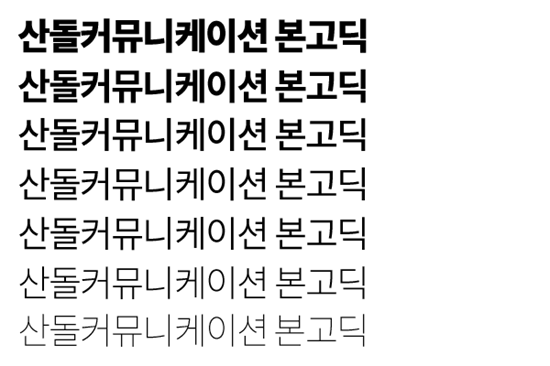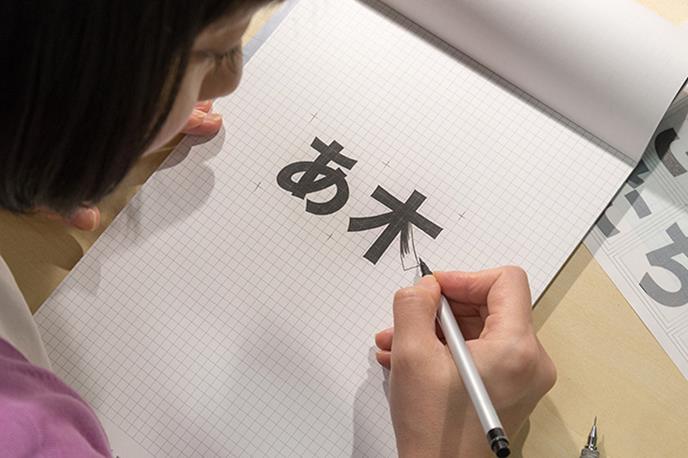
산돌+Adobe+Google, 글로벌 오픈소스 서체 ‘본고딕’ 출시
산돌커뮤니케이션(이하 산돌)이 Adobe, Google과 함께 한중일 오픈 소스 서체인 ‘본고딕(Source Han Sans)’을 7월 16일 출시했다. 성공적인 한중일 통합서체 개발을 위한 본고딕 프로젝트는 산돌커뮤니케이션이 한글 제작에 참여하였으며 일본의 이와타, 중국의 창저우 시노타입 등 총 5개 기업의 공동작업 형태로 진행됐다.
Adobe-Google-산돌, 공동 프로젝트로 뭉치다
사회 환원의 비전을 가진 Adobe는 ‘누구나 사용 가능한 오픈 소스 서체 개발’에 지속적 관심을 가지고 있었고 Google 역시 같은 뜻으로 본고딕 프로젝트에 함께했다. 전세계 모든 정보를 체계화해 언제 어디서 누구든 용이하게 정보에 접근하게 하는 것이 Google의 목표이기 때문이다.
성공적인 한중일 통합서체 개발을 위한 본고딕 프로젝트는 산돌커뮤니케이션이 한글 제작에 참여하였으며 일본의 이와타, 중국의 창저우 시노타입 등 총 5개 기업의 공동작업 형태로 진행됐다. 개별 서체의 퀄리티는 물론 서로 다른 언어의 서체가 한데 어우러졌을 때의 조화까지 고려해야 하는 만큼, 서체 개발업계에서도 매우 드문 기획이었으며 그만큼 많은 이들의 이목을 집중시켰다.
본고딕은 어떤 서체인가?
▲ 다양한 언어로 쓰인 본고딕 (이미지 출처 – Typekit Blog)
▲ 위쪽부터 Heavy, Bold, Medium, Regular, Normal, Light, ExtraLight
본고딕은 한국어, 일본어, 중국어 번체, 중국어 간체, 라틴어, 그리스어, 키릴 자모가 모두 포함된 글로벌 오픈 소스 서체다. 언어 당 65,535개의 글립(Glyph, 글자 하나의 모양에 대한 기본 단위)이 포함되고 모든 언어를 합쳐 총 50만개 글립에 이르니, 지금까지 제작된 서체 중 최대 규모라 할 수 있다. 더불어 모든 언어의 서체가 각각 ExtraLight, Light, Normal, Regular, Medium, Bold, Heavy의 7가지 굵기를 가지고 있어 더욱 폭넓게 사용할 수 있다.
▲ 본고딕 서체 디자인 작업을 하고 있는 료코 니시즈카의 모습 (이미지 출처 – Typekit Blog)
기능 및 디자인 측면에서 본고딕을 키워드로 표현하자면 바로 ‘가독성’과 ‘우아함’. 간소화된 자획과 일관된 두께로 태블릿 PC나 모바일 등 작은 화면과 장문의 텍스트에서 가독성을 살린다. 그에 더해 간소화된 형태에도 불구하고 전통 고딕 서체 본연의 우아함을 잃지 않았다는 평가도 얻고 있다. 또한 아시아권을 아우르는 한중일 통합 서체답게 지역에 따른 한자 글꼴 차이를 완벽하게 지원하며, 서로 다른 언어의 서체를 사용해도 조화를 잃지 않으니 글로벌 컨텐츠를 제작해야 하는 디자이너들을 만족시킬 수 있을 것으로 예상된다.
Adobe-Google-산돌, 본고딕에 관한 말말말
본고딕의 저작권을 소유한 Adobe는 검증된 서체 디자인 경험을 바탕으로 자동화 등 전문 기술을 제공했다. Adobe 서체 개발 수석 켄 룬드 박사는 “본고딕이라는 오픈 소스를 통해 콘텐츠 제작자가 원활하게 작업하고, 동아시아 사용자에 수준 높은 서비스를 제공할 수 있을 것”이라고 말했다. 이로써 본고딕은 Adobe 창립 25주년을 맞이해 101번째 Adobe 오리지널 서체가 되었다.
Google은 적극적 의견, 리소스, 전문 기술, 자금까지 본고딕 제작 프로젝트에 아낌없는 지원을 했다.또한 자사의 노토 통합유니코드 서체 모음의 일부로 ‘Noto Sans CJK’라는 이름으로 본고딕 자체버전을 출시할 예정이다. 리누스 업슨 Google 엔지니어링 담당 부사장은 “이 서체가 노토 모음에 추가됨으로써 모든 언어를 완벽하게 지원하고자 하는 구글의 목표에 한층 더 다가갈 수 있게 됐다”고 기대했다.
그렇다면 산돌커뮤니케이션은 어떻게 본고딕 프로젝트에 동참하게 되었을까? 수 년 전 Adobe가 CJK프로젝트를 담당할 한국 서체기업을 물색하던 중 MS사 ‘맑은고딕’과 Apple사 ‘SD산돌고딕네오’등 산돌이 개발한 서체의 우수성을 인정받아 함께 프로젝트를 진행하게 되었다. 이후 약 2년의 작업 끝에 출시된 것이 바로 이번에 출시된 본고딕이다.
▲ 산돌커뮤니케이션이 제작한 MS사의 맑은고딕
▲ 기존 애플고딕(좌)와 산돌커뮤니케이션이 제작한 애플SD고딕네오(우)
한글 및 옛한글 제작을 담당한 산돌은 Adobe측 담당자와 메일을 통해 의견을 주고받으며 프로젝트를 진행했으며, 필요에 따라 각국 개발사 및 Google과도 디자인 및 기술적 이슈를 해결하며 글로벌 서체 개발 기업으로서의 역할을 했다. 본고딕의 한글 서체를 담당한 장수영 디자이너는 “각 언어권의 폰트 전문가들이 모여 하나의 통합 폰트를 제작한 것에 큰 의미가 있다”며 “이번 프로젝트가 표기의 통일성 측면에서 서체 개발사들이 모색해야 할 시발점이라고 생각한다”고 참여 소감을 전했다.
본고딕의 사용범위는?